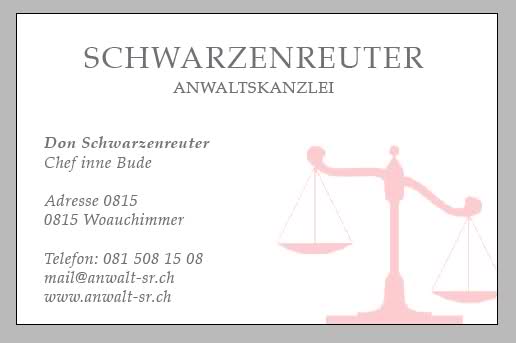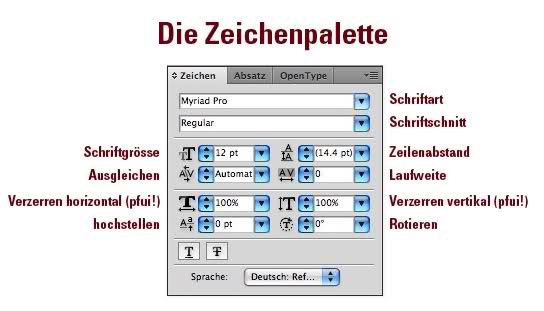
Fragen zur Typographie
Warum nimmst Du nicht einfach den Schriftzug so wie er ist und
setzt die Waage – und zwar eine klassische, geschwungene wie bei
einem der ersten HDS Versuche – als Stilelement ein z.B. 20% rot
in den Hintergrund? Das könnte man wunderbar auf alle möglichen
Drucksachen adaptieren. Mit ein bisschen Fantasie sogar sehr kreativ.
Im Anhang mal was schnell gebasteltes. Null ausgeglichen und das
Bild rotzfrech bei google geliehen. Layout Katastrophe. Ist aber
auch nur zur Veranschaulichung meiner Gedankengänge mit den
Stilelementen für Drucksachen
den Ansatz zur Reduktion kann ich nur unterstützen. Denn die Auszeichnung eines Buchstabens, der sich nur durch die Ähnlichkeit mit der Waage hervortut, nicht in der Wortmitte steht und sonst keine Verbindung zu Namen, Tätigkeit etc. aufweist, kann so nicht funktionieren.
Das mit der Waage wird wohl nichts, die würde ich abstrahieren, vereinfachen, nur ein Detail zeigen.
Ich denke, es zeigt sich, wie schwierig gutes Logodesign ist. Ich sehe das täglich bei nahmhaften Gestaltern: zwanzig, dreissig gescribbelte Ideen (und zwar Ideen und nicht nur Formen/Buchstaben rumschieben) von denen die Meisten im Müll landen und hier ebenso gnadenlos verrissen würden.
Tschio geht wohl den falschen Weg, wenn er meint, er könne eine Schnellbleiche zum Typogestalter/Grafiker anhand eines Logodesigns durchziehen, ohne sich die nötigen Grundlagen zu beschaffen. Und das heisst halt auch: Lesen, anschauen, vergleichen, verwerfen, neu beginnen. Ohne die Fähigkeit, selber zu sehen, wie sich etwas zu Besseren entwickelt und bei jedem Versuch wieder fragen zu müssen «was meint ihr dazu ...?» steht er auf verlorenem Posten.
hier mal ein Versuch.
Ich habe den Schriftzug als "BOLD" ausgewählt, damit man die Waage besser erkennt wegen des weißen Randes.
Bei Visitenkarten setze ich die Waage seperat.
Buchstaben ausgeglichen unter (Fenster,Schrift,Zeichen, dann "Optisch")
Das "Rot" = CMYK C=0, M=100, Y=100, K=0 und Deckkraft mit 30%
2-Farben-Logos, insbesondere mit Grau, sollten nicht in CMYK sondern
mit (Pantone-) Volltonfarben definiert werden. Damit wird Grau nicht
gerastert sondern als Vollfläche «mit der Farbe grau» gedruckt. Noch-
mals: ohne Grundwissen hast Du keine Chance! Deckkraft rastert nur
die Farbe. Also unlesbar bei kleiner Schrift wie z.B. auf Visitenkarten.
Ausgleichen geht auch nicht mit der Einstellung «optisch» automatisch.
Die Einstellung bezieht sich nur auf den Ausgleich bei normalem Lauf-
text. Die Buchstaben bei VERSAL gesetzten Logos müssen manuell (!)
ausgeglichen werden. Da führt kein Weg daran vorbei. Siehe Bild unten,
links ist Buchstaben ausgleichen, rechts die Gesamt-Laufweite (also
mehr Raum zwischen alle Zeichen gleichzeitig)
Die Waage ist zudem lizenzrechtlich geschützt (ja, google-Bilder sind
tabu…) und eigentlich wie oben bereits erwähnt nicht nötig oder nicht
passend. Too much, eben… Der Schriftzug alleine wirkt – wenn Du
etwas mehr Laufweite gibst – für sich selbst sehr elegant. Also genau
das, was Du willst. Bold verliert die Schrift ihre Eleganz und wird wuchtig.
Zum Verständnis der Fachbegriffe habe ich die Schrift-Palette mal
mit Beschriftungen versehen. Ausdrucken, auswendig lernen ;-)
Verzerren ist typografisch praktisch gar nie angebracht und für mich eine Sünde.
Dafür kommt man in die WordArt Hölle mit Schlagschatten und Verläufen!
Mach was aus diesen Infos! (Den vernünftigen über dem Bild natürlich…)
hier mal ein Versuch.
Die Waage, die von ihrer inneren Logik her stehen müßte, »hängt« optisch unter der Schrift.
Vielleicht mal die Anordnung
Waage
HERBSTREUTHER
ANWALTSKANZLEI
versuchen. Dann würde die Waage sozusagen auf der statischen, breiten Zeile »HERBSTREUTHER« stehen.
Der Ausgeich von »ANWALTSKANZLEI« geht übrigens gar nicht. Die engste Stelle ist ausgerechnet die Wortfuge zwischen S und K, während danach, zwischen K und A ein gigantisches optisches Loch klafft.
In Illustrator sind unter Farbfeldbibliotheken jede menge Pantonene Volltonfarben hinterlegt, welche nehme ich da dann?
Professionell suchst du dir die aus einem Pantone Farbfächer aus, der kostet allerdings sein Geld.
Weniger professionell verlässt du dich auf das, was dein Bildschirm dir anzeigt, und suchst die Farben aus die dir gefallen.
Dich habe ich vergessen, sorry, habe das Wort "Herbstreuter" optisch nicht metrisch spazioniert. Kann ich dies so lassen oder war das zu viel oder zu wenig ?